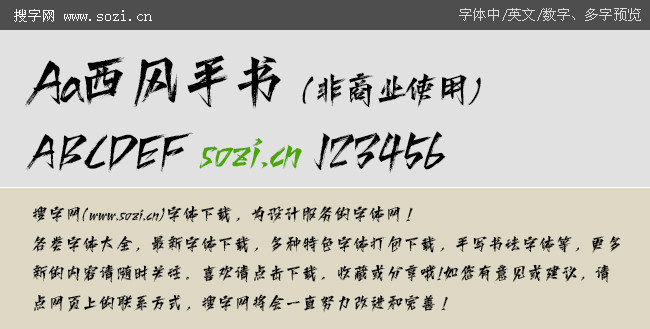
Aa西風(fēng)手書(shū)
搜字網(wǎng)給大家提供一款A(yù)a西風(fēng)手書(shū)(非商業(yè)使用)中文字體下載,該字體是一款手寫(xiě)書(shū)法中文字體,字跡飛揚(yáng),筆斷意連,傳統(tǒng)與現(xiàn)代的手寫(xiě)結(jié)合,適合書(shū)裝設(shè)計(jì)、包裝設(shè)計(jì)、海報(bào)設(shè)計(jì)等應(yīng)用(此字體為個(gè)人非商用版,商用可以聯(lián)系QQ:1006760504)。